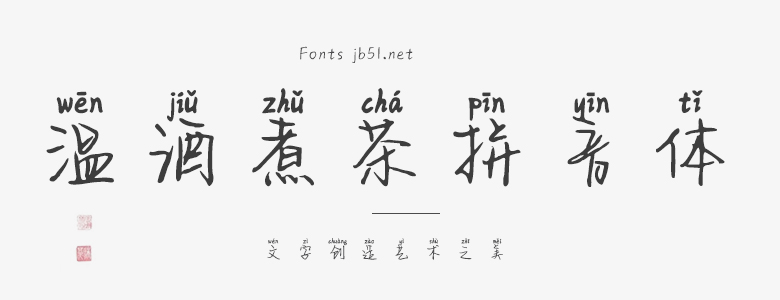
溫酒煮茶拼音體是一款獨(dú)具特色的字體,其設(shè)計(jì)靈感來源于中國傳統(tǒng)文化的博大精深和豐富內(nèi)涵。該字體將傳統(tǒng)書法元素與現(xiàn)代設(shè)計(jì)理念相結(jié)合,呈現(xiàn)出既有古典韻味又不失現(xiàn)代感的獨(dú)特風(fēng)格。 字體設(shè)計(jì)細(xì)節(jié)豐富,每個(gè)字母都經(jīng)過精心的打磨和調(diào)整,使字體看起來既有藝術(shù)性又易于閱讀。溫酒煮茶拼音體的字母形狀優(yōu)雅,線條流暢,呈現(xiàn)出一種柔和舒適的視覺感受。該字體的設(shè)計(jì)旨在傳達(dá)中華文化的獨(dú)特魅力,同時(shí)為現(xiàn)代設(shè)計(jì)增添新的元素。 溫酒煮茶拼音體適用于多種場合和媒介,無論是用于紙質(zhì)書籍的印刷,還是電子設(shè)備的顯示,都能呈現(xiàn)出清晰、優(yōu)美的視覺效果。該字體適合用于需要展現(xiàn)中國傳統(tǒng)文化氛圍的文本,如詩詞、古文、武俠小說等。同時(shí),其優(yōu)美的線條和柔和的視覺感受也使其適用于制作溫馨、浪漫的氛圍。 總之,溫酒煮茶拼音體是一款富有文化內(nèi)涵和藝術(shù)性的字體,它將傳統(tǒng)與現(xiàn)代相結(jié)合,展現(xiàn)了中華文化的博大精深。無論是在閱讀還是在欣賞方面,都能帶給人們一種獨(dú)特的視覺享受。